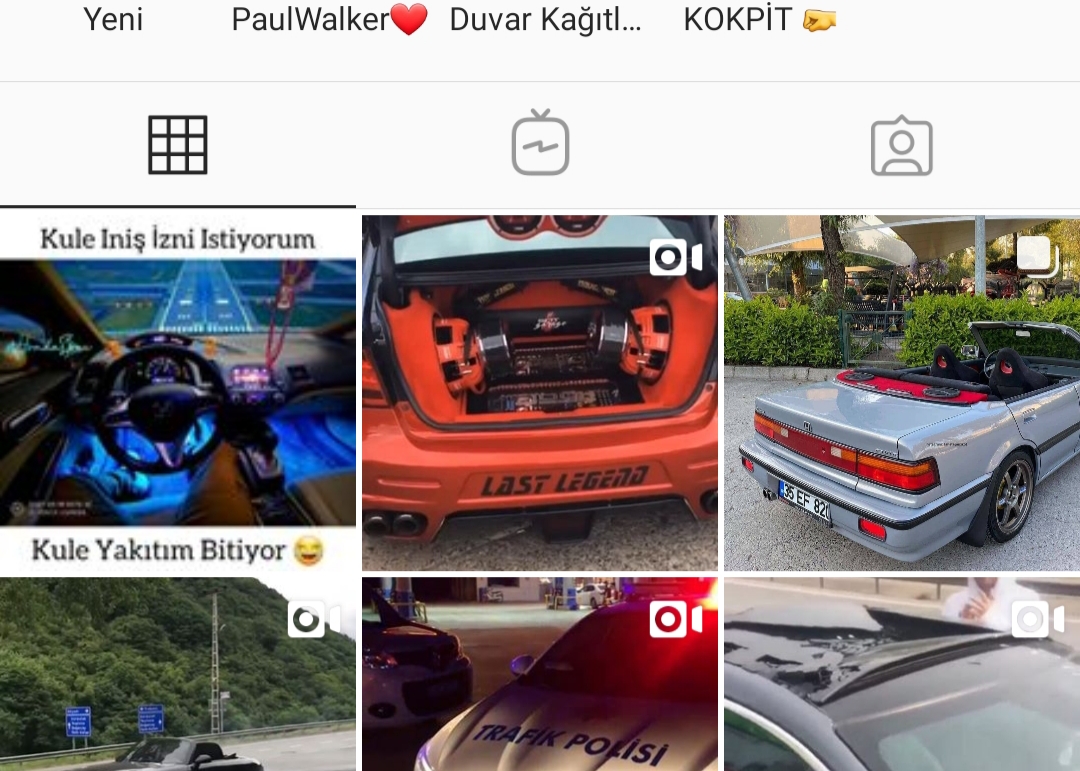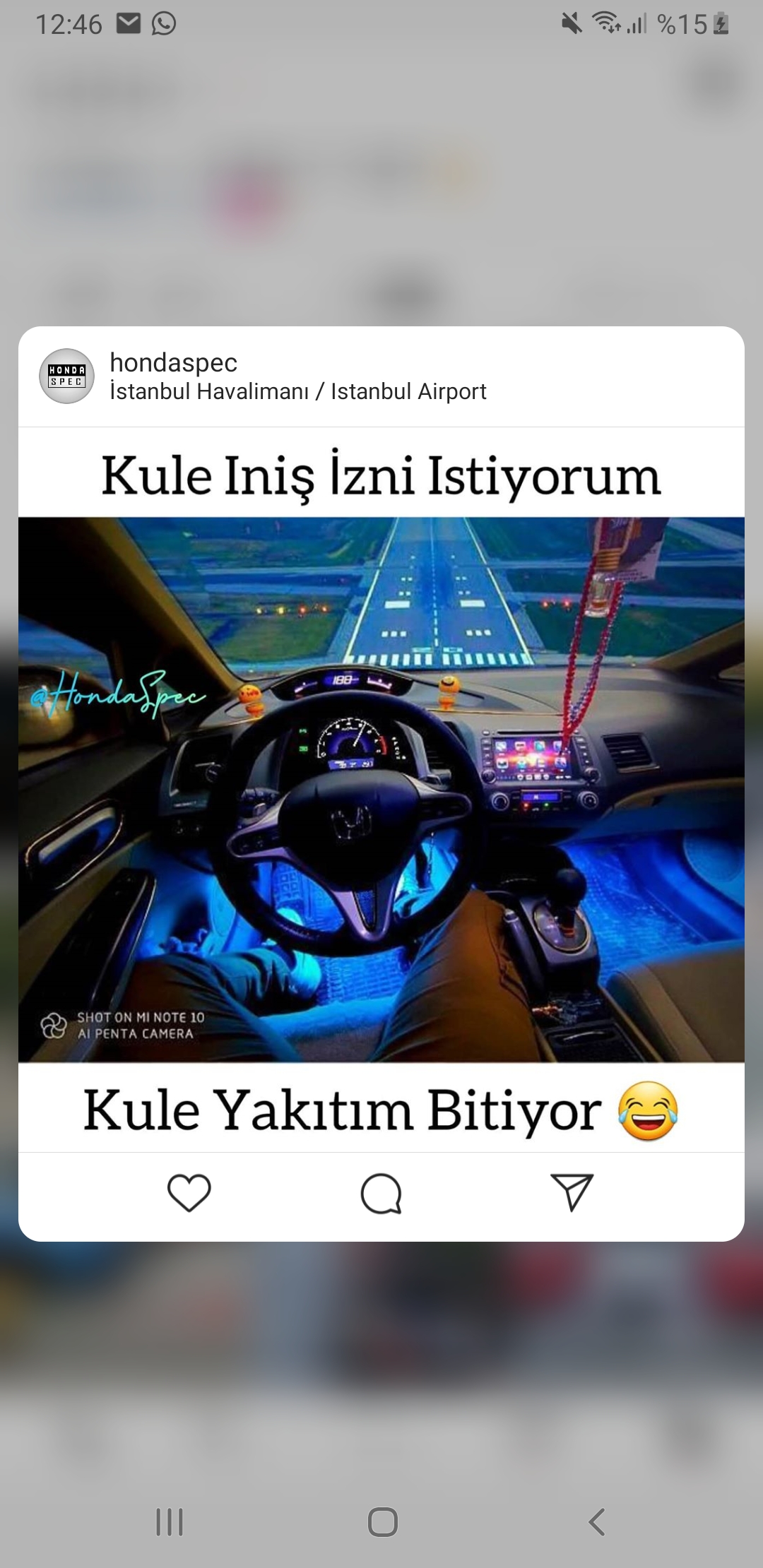
Kule Inis İzni Istiyorum ve Kule Yakıtım bitiyor yazan yerler için sayfaya yakışacak güzel bir font arıyorum var mı önerisi olan? Bu arada resmin içinde sol tarafta bulunan resim içi yazı içinde font önerisi alabilir miyim?
Sayfa profilinde uzaktan böyle duruyor okunabilir olması daha güzel olacaktır
Nexabold bence güzel bir font hocam. İnstagram postlarında da çok kullanılıyor.